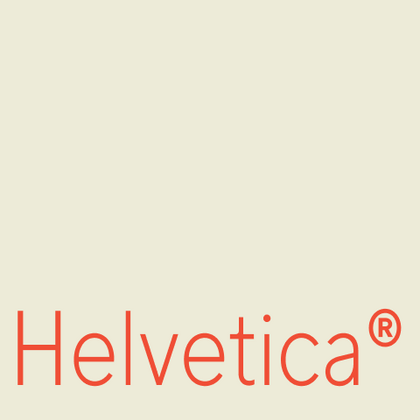
Шрифты похожие на Helvetica
Если вы устали от «заезженных» шрифтов и ищете гарнитуры, похожие на Helvetica, ознакомьтесь с нашими лучшими альтернативами. Как и шрифт Helvetica®, наши шрифты из подборки — неогротески с нейтральным характером, ровными пропорциями и закрытыми контурами.
В коллекции TypeType представлены шрифты, которые сохраняют фирменную «геометрию» Helvetica®. Используйте альтернативный вариант от TypeType для цифровых продуктов, брендинга (узнаваемость + свежесть), или типографики премиум-класса (точные пропорции),
Если вы устали от «заезженных» шрифтов и ищете гарнитуры, похожие на Helvetica, ознакомьтесь с нашими лучшими альтернативами Helvetica. Это шрифты, которые имеют близкие характеристики, но в то же время обладают новыми уникальными особенностями дизайна. Например, относятся к той же категории шрифтов, подходят для тех же целей и имеют похожие черты, но отличаются в деталях или пропорциях.
В TypeType вы найдете передовые шрифты, такие как Helvetica и даже лучше: вот несколько замечательных и не столь распространенных альтернатив Helvetica. Используйте этот список высококачественных, выглядящих как Helvetica шрифтов, на свой вкус. Так вы сможете подобрать еще более для вашего проекта подходящий шрифт, расширив выбор, или освежить свой дизайн. Все шрифты, представленные в этой коллекции, доступны в разных форматах и по доступным ценам, поэтому вы сможете найти тот, который соответствует любым потребностям!
Найдите отличную замену Helvetica и попытайтесь имитировать похожее настроение, передать нужное вам ощущение, используя его в своих проектах. Каждый шрифт, представленный на этой странице, является двойником шрифта Helvetica, фактически его полным аналогом.
TT Turns — геометрический гротеск с акцентными круглыми знаками и выразительными нависающими элементами. Это универсальный шрифт, который лаконично выглядит и отлично читается в маленьком размере, при этом в крупных кеглях становится акцидентным и проявляет свой характер на максимум. Он энергичный, сильный и динамичный — особенно отчётливо это проявляется в наклонных начертаниях.
TT Firs Neue — скандинавский гротеск, сочетающий выразительные графические элементы с универсальностью использования. Мы проанализировали каждый контур и графический элемент. Пересобрали шрифт заново, чтобы сохранить лучшее и исправить необходимое.
TT Fellows — гуманистический гротеск с механистическими мотивами. Открытые формы, дружелюбно-нейтральный характер тонких весов и ещё более мягкий характер в жирных начертаниях.
TT Interphases Pro — неогротеск, который создавался специально для работы в интерфейсах. Среди визуальных особенностей TT Interphases Pro — плавные формы скруглений, повторяющиеся во всех элементах: благодаря им большие массивы текста читаются легко и приятно.
TT Paplane — акцидентный сквадраченный гротеск. Так, характерные черты этого гротеска — сквадраченные формы, 45-градусные срезы и обтекаемые внешние контуры.
TT Travels Text — геометрический гротеск с широкими пропорциями. Основные визуальные отличия TT Travels Text — достаточно широкие пропорции и немного сквадраченные формы овалов.
TT Firs Text создавался на основе обновленной в 2023 году гарнитуры TT Firs Neue. Мы сохранили эстетику скандинавского минимализма, но полностью перерисовали все выразительные элементы, сделав их более мягкими и традиционными.
TT Rounds Neue — гротеск со скругленными формами. В тонких начертаниях шрифт выглядит довольно минималистично и нейтрально: скругленные окончания штрихов становятся практически незаметными, на первый план выходят плавные линии.